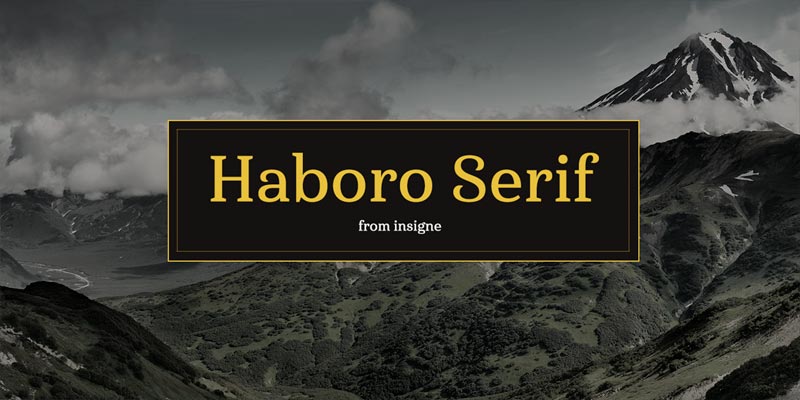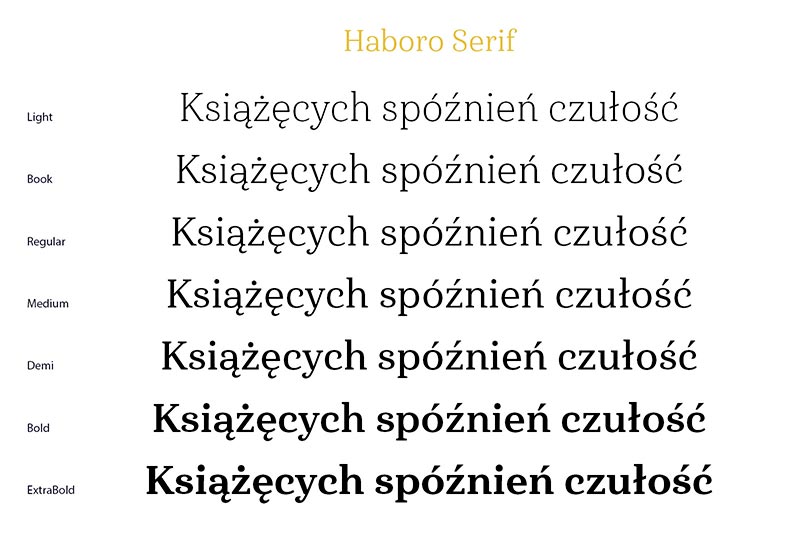
Font Haboro Serif
Do naszego studia trafił font Haboro Serif, będący uzupełnieniem podstawowej wersji Haboro. Został zaprojektowany w 2016 roku przez Jeremiego Dooleya  z USA. Haboro Serif to 42 odmiany wysokiej jakości szeryfowych fontów, nadających się znakomicie do składu książek i czasopism.